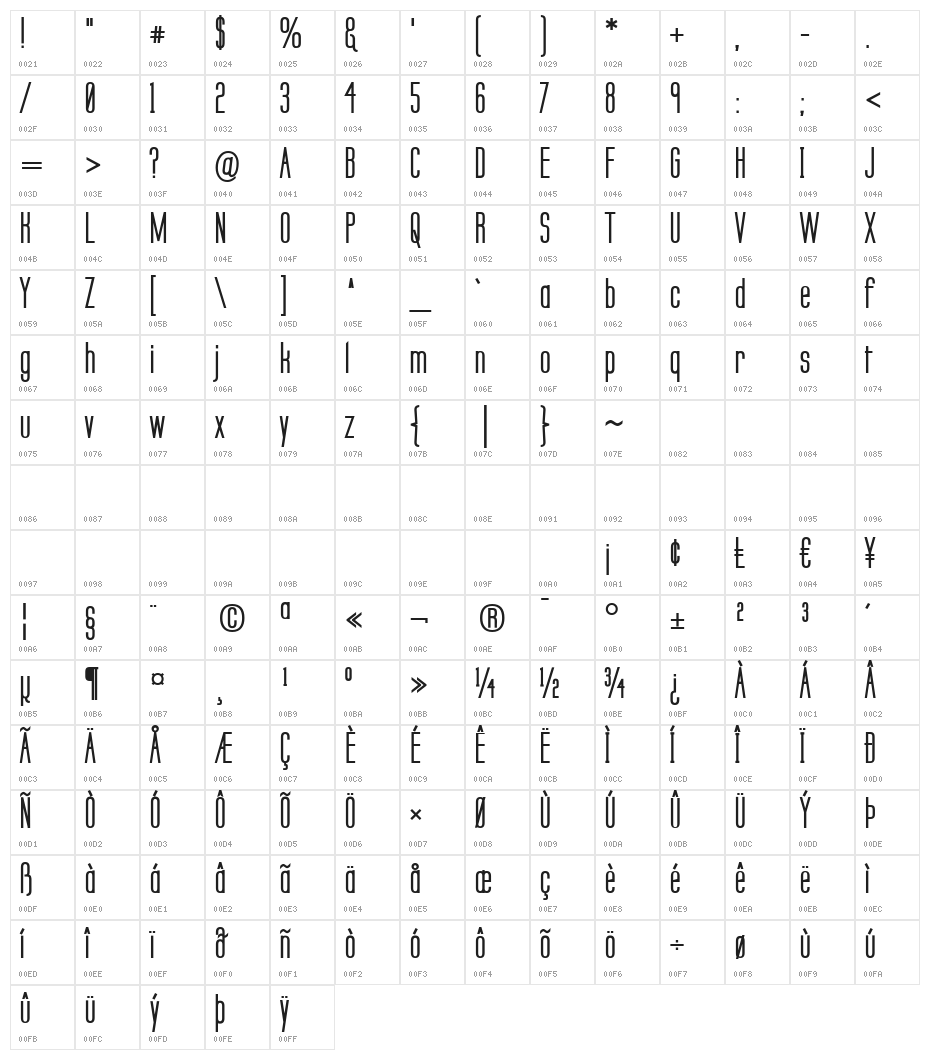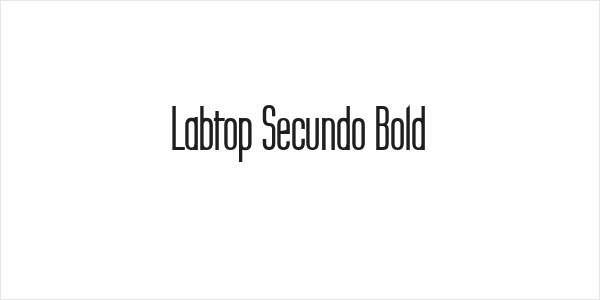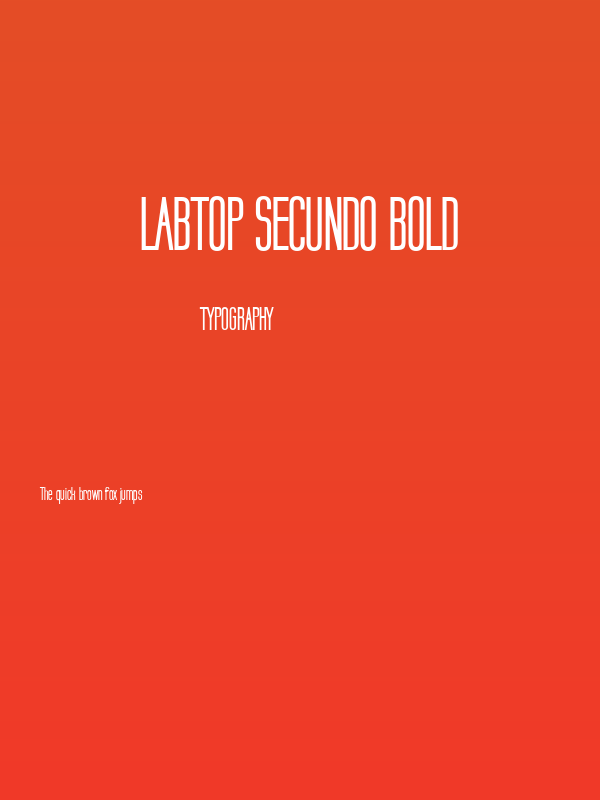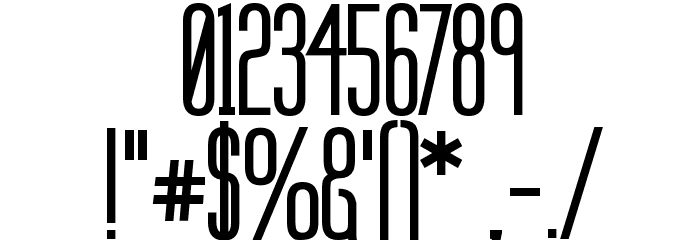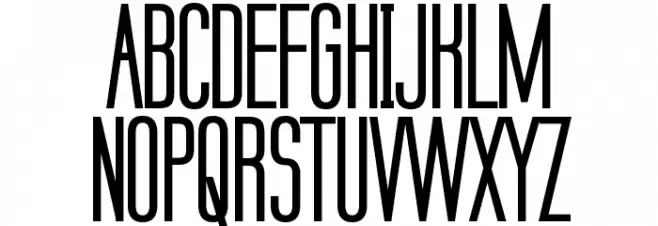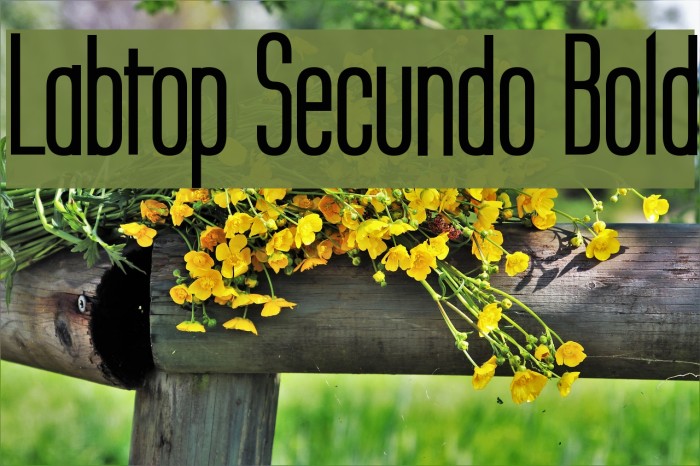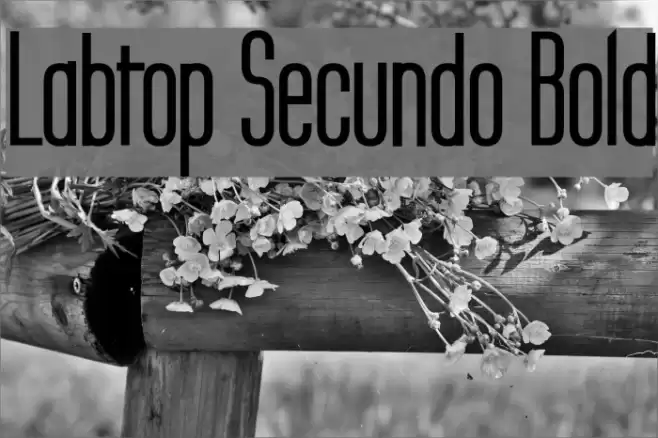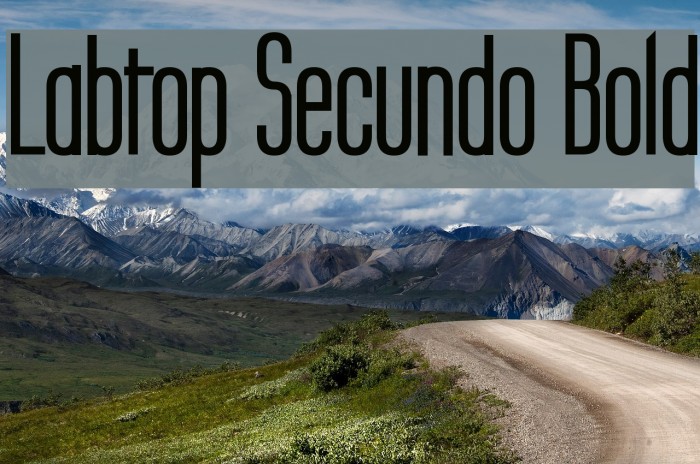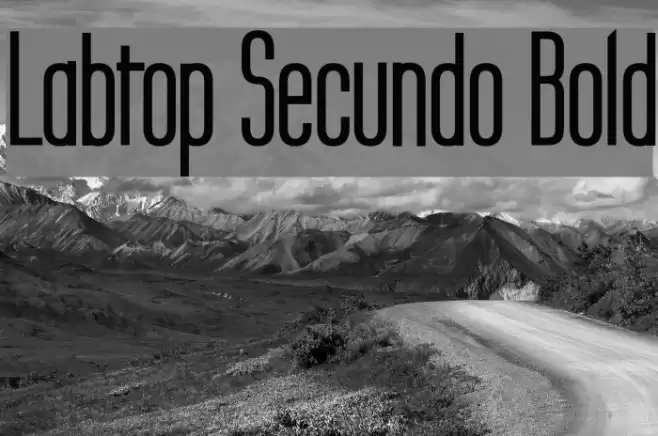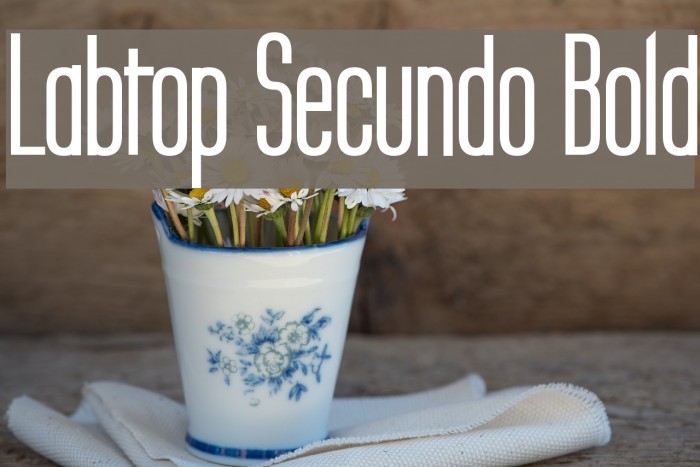
Labtop Secundo Bold Font
| おすすめプロジェクト | Ideal for modern branding, fashion magazines, posters, and digital media where a bold, stylish statement is needed. |